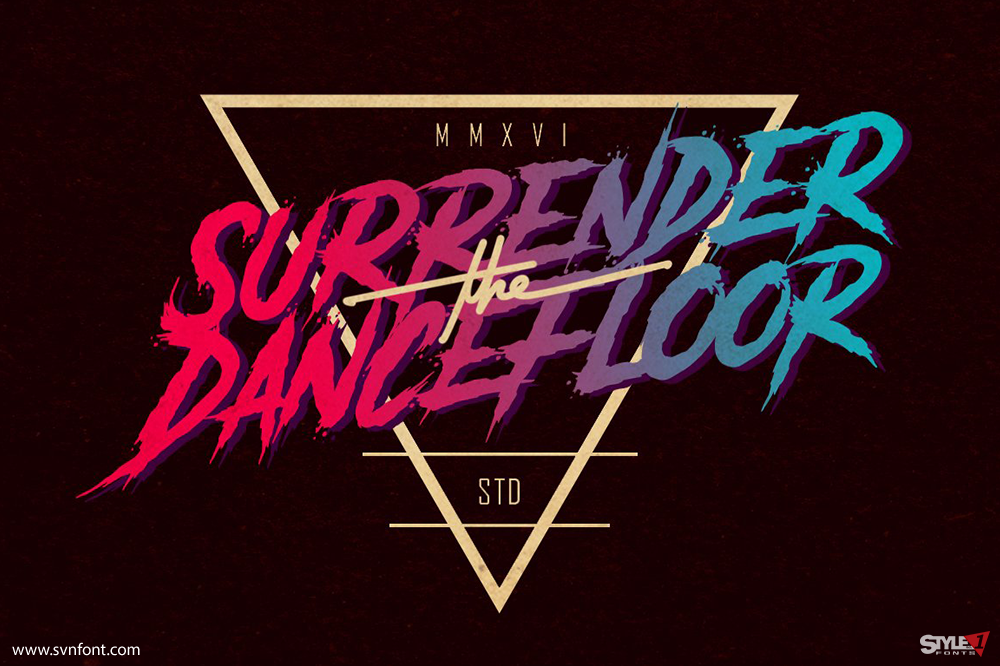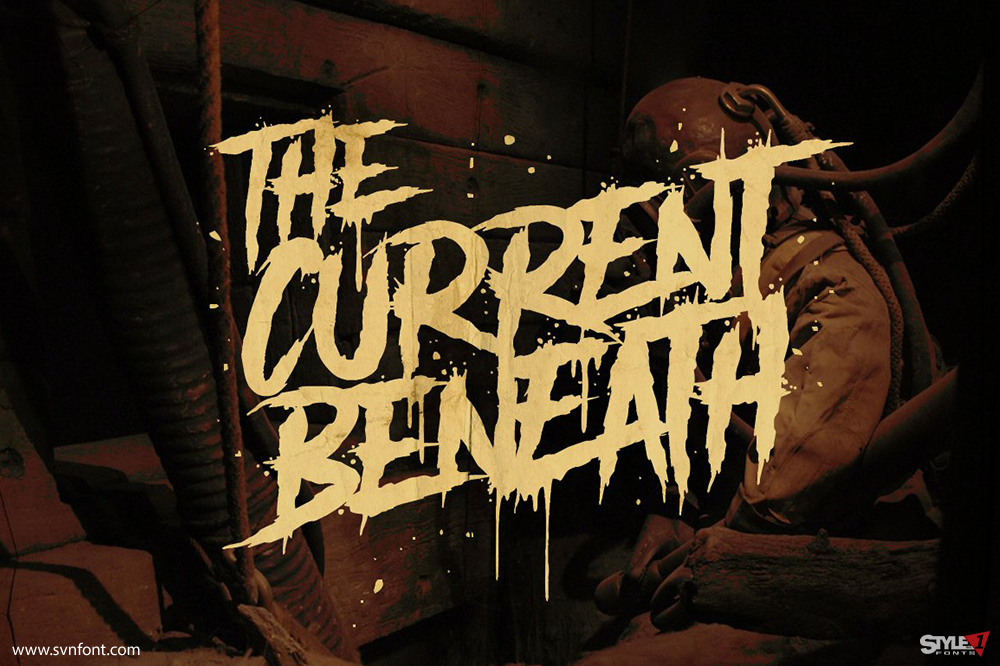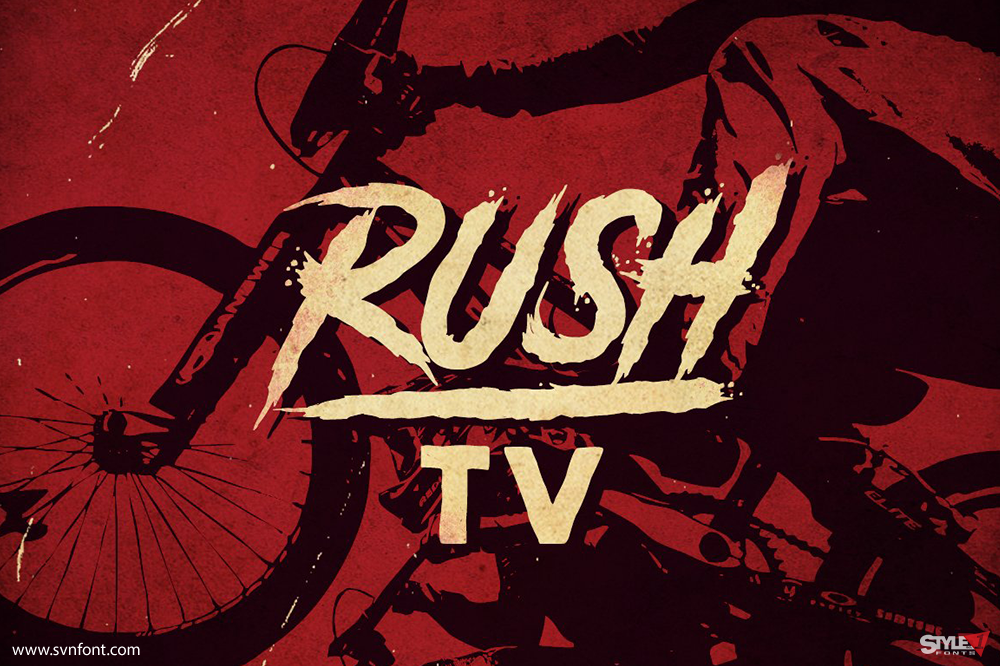
Kiểu chữ chứng tỏ sự hữu ích của nó theo thời gian. Với những vết mực ngẫu hứng được đưa vào từng ký tự, nó tạo ra một sự bí ẩn. Mang đến cảm giác hardcore, phong cách retro, những tác phẩm nghệ thuật của sự hỗn loạn. Hãy thỏa sức sáng tạo của bạn với Another Danger!
Nhà thiết kế: The Branded Quotes
Nhà phát hành: The Branded Quotes